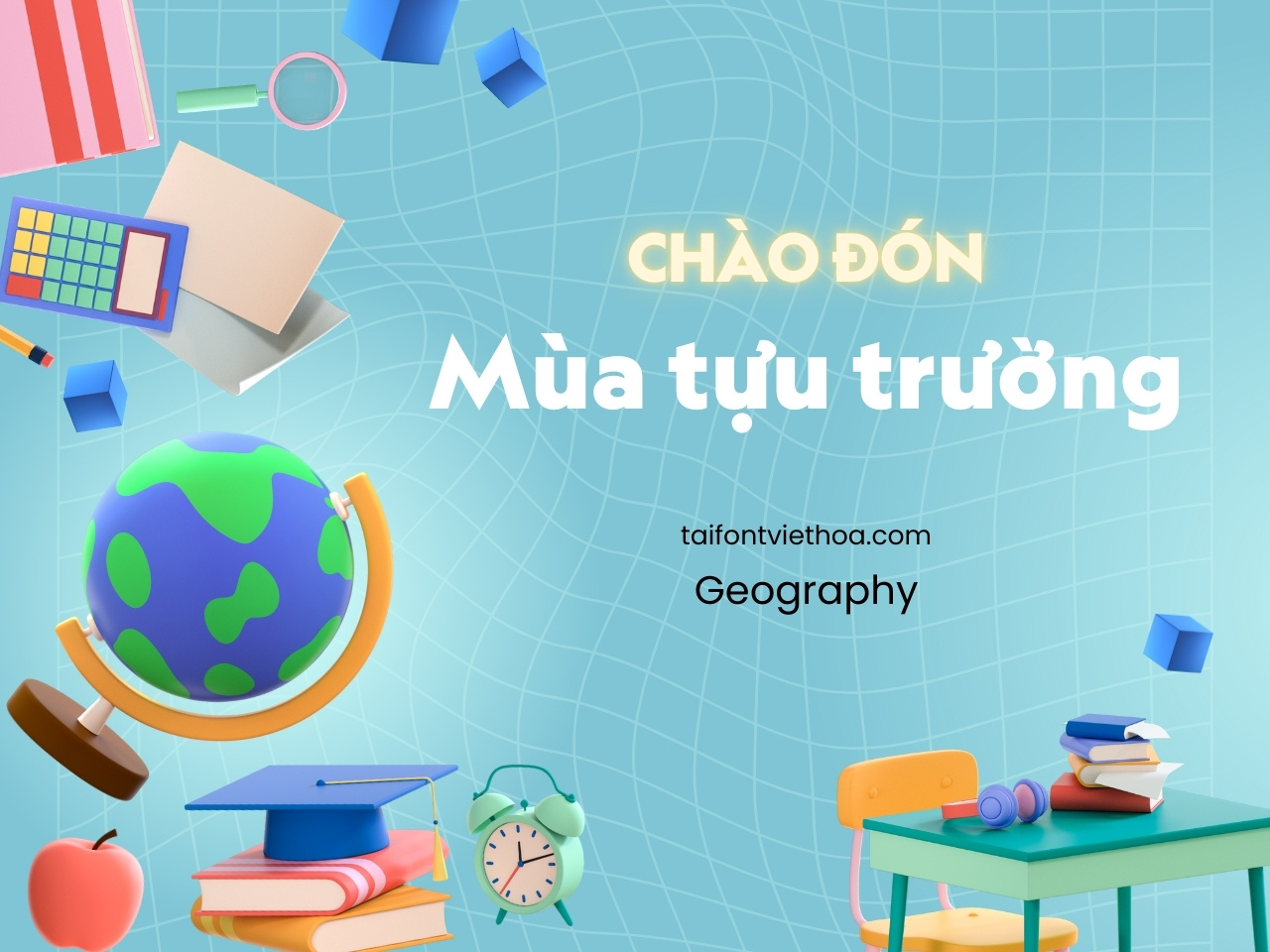
Font việt hóa Geography
Giới thiệu font Geography – Phong cách hiện đại, cân đối và thân thiện
Geography là một kiểu chữ sans-serif hiện đại, được thiết kế với tiêu chí cân bằng giữa tính học thuật và ứng dụng thực tế trong thiết kế đồ họa. Font có nguồn gốc từ phong cách hình học, mang dáng vẻ chuyên nghiệp nhưng vẫn giữ được sự mềm mại và thân thiện với người đọc. Phiên bản Việt hóa được thực hiện bởi Tavan Phuc, hỗ trợ đầy đủ tiếng Việt và hơn 100 ngôn ngữ khác trên toàn cầu. Đây là một bộ font lý tưởng dành cho cả môi trường giáo dục lẫn các ứng dụng truyền thông hiện đại. Font đã được taifontviethoa.com chọn lọc, sưu tầm và chia sẻ nhằm phục vụ cộng đồng thiết kế Việt trong nhiều lĩnh vực đa dạng – từ học tập, truyền thông cho tới nhận diện thương hiệu.
Đặc điểm thiết kế thân thiện và ứng dụng rộng rãi của Geography
Geography sở hữu cấu trúc chữ rõ ràng, đường nét gọn gàng, tròn trịa và tỷ lệ ổn định – tạo nên khả năng đọc tốt trên cả văn bản dài và tiêu đề ngắn. Font rất phù hợp cho các thiết kế tài liệu giáo dục, website trường học, app học tập, bảng thông tin, slide thuyết trình, bao bì thực phẩm và các sản phẩm dành cho cộng đồng. Tính đa dụng và dễ ứng dụng khiến Geography trở thành lựa chọn tối ưu cho các ngành như giáo dục, ẩm thực, bất động sản, truyền thông xã hội và các dịp như ngày Nhà giáo, sinh nhật hoặc các chiến dịch quảng bá sản phẩm mới.